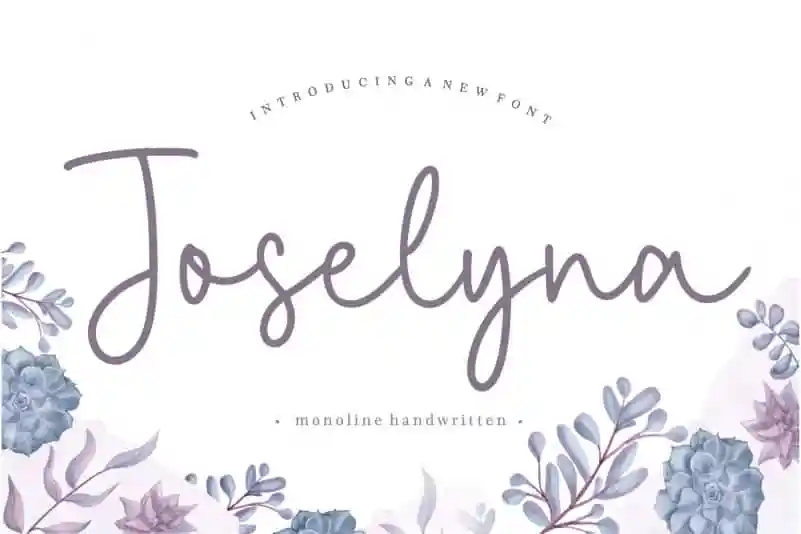
Joselyna Monoline Handwritten Font – Download Grátis
A ‘Joselyna Monoline Handwritten Font’ é uma escolha irresistível para quem busca transparência e elegância no design de materiais impressos ou digitais. Conhecida por seu estilo natural e autêntico, essa fonte proporciona um toque suave às criações, tornando-a perfeita para aplicação em elementos como embalagens de produtos, identidades corporativas, revistas, mídia social, convites para casamentos ou qualquer projeto onde se deseja expressar suas ideias acima do fundo. Com uma escrita cuidadosamente elaborada que transmite confiança e simplicidade sem esforço, a Joselyna Monoline é ideal para aqueles que valorizam um design minimalista mas não dispensam o toque pessoal. Suas linhas leves e harmoniosas são especialmente adequadas para estilos de marca inovadores ou criações gráficas onde deseja-se criar uma conexão forte com os consumidores, deixando seu design imprimindo sua essência sem comprometer a importância da palavra. Com a Joselyna Monoline, você pode experimentar o equilíbrio entre modernidade e originalidade em suas próximas criações. Não importa o tipo de projeto para o qual você está aplicando esta fonte, é uma escolha que certamente não fará você se arrepender.